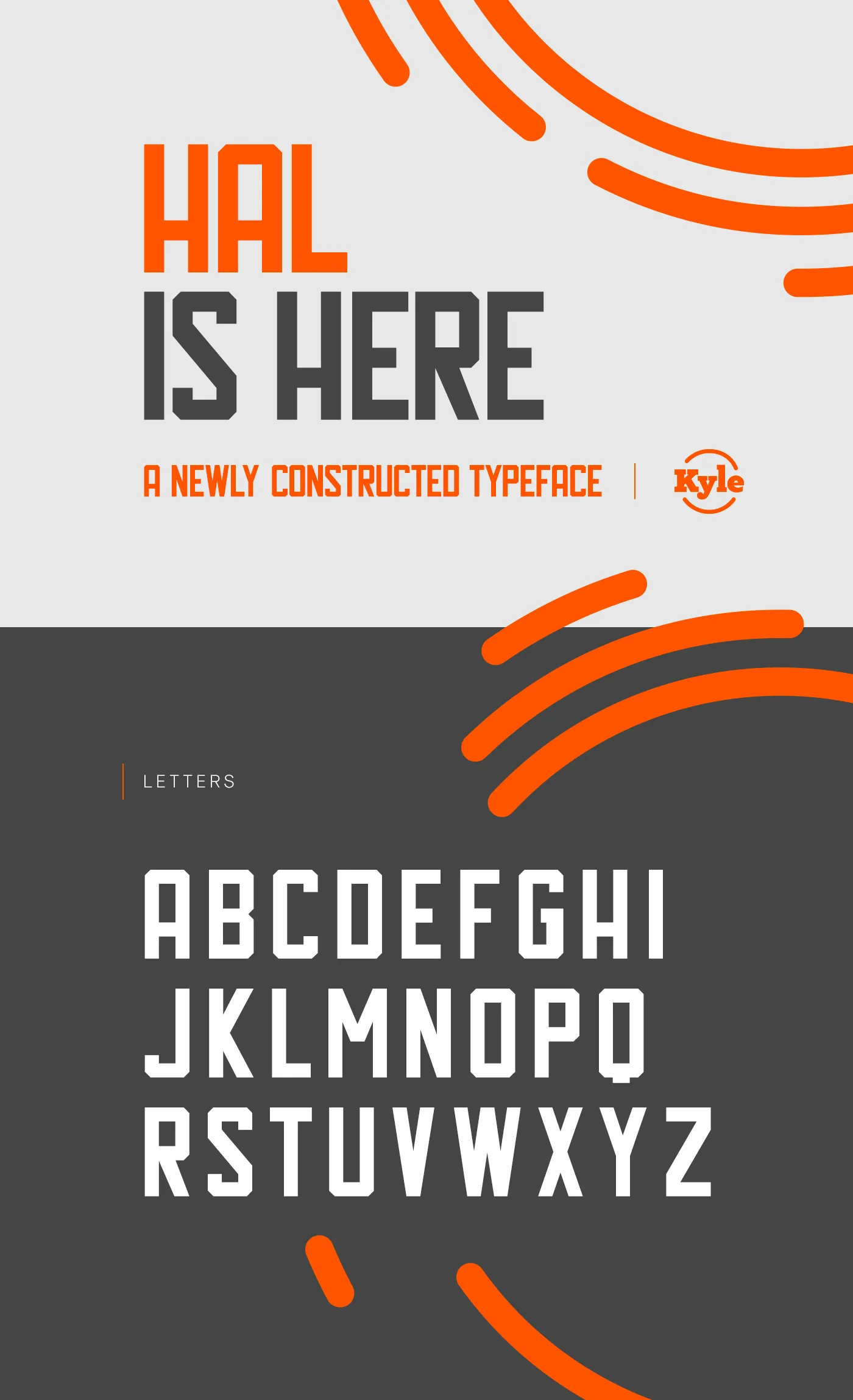
A Hal Typeface é uma nova família de tipo geométrico, criada pelo designer Hamilton para a fonte livre introduzida pela Hal typeface. Inspirada nos dígitos eletrônicos e sem serifas, esta fonte destaca-se por sua simplicidade única, ao mesmo tempo dinâmica e versátil, com múltiplas opções de suporte linguístico que a tornam ideal para diversas aplicações gráficas. A Hal oferece apenas um peso da tipografia, mas é uma escolha incrível para quem busca um olhar moderno e minimalista em seus projetos digitais ou impressos. Com sua simplicidade e característica distintiva, a fonte conquistará qualquer design que ela se encaixar.